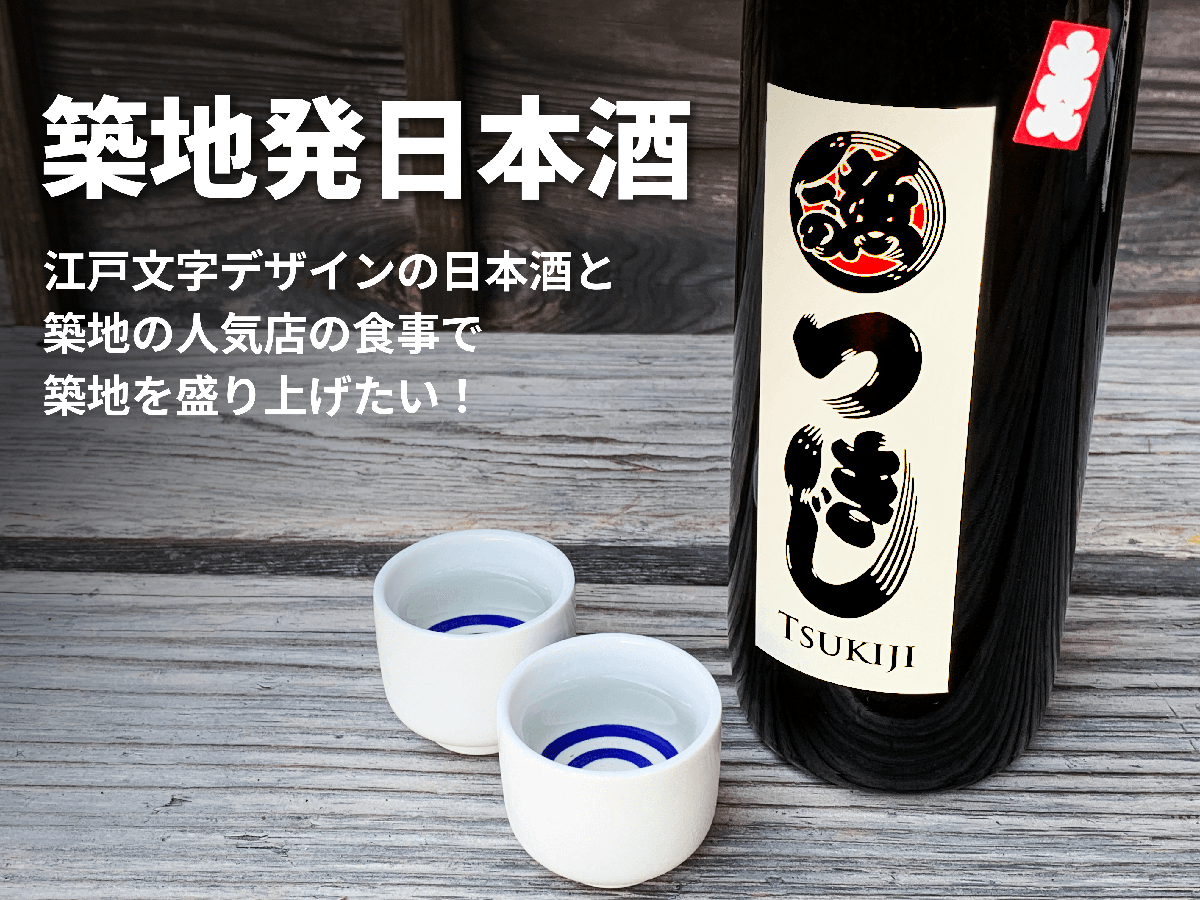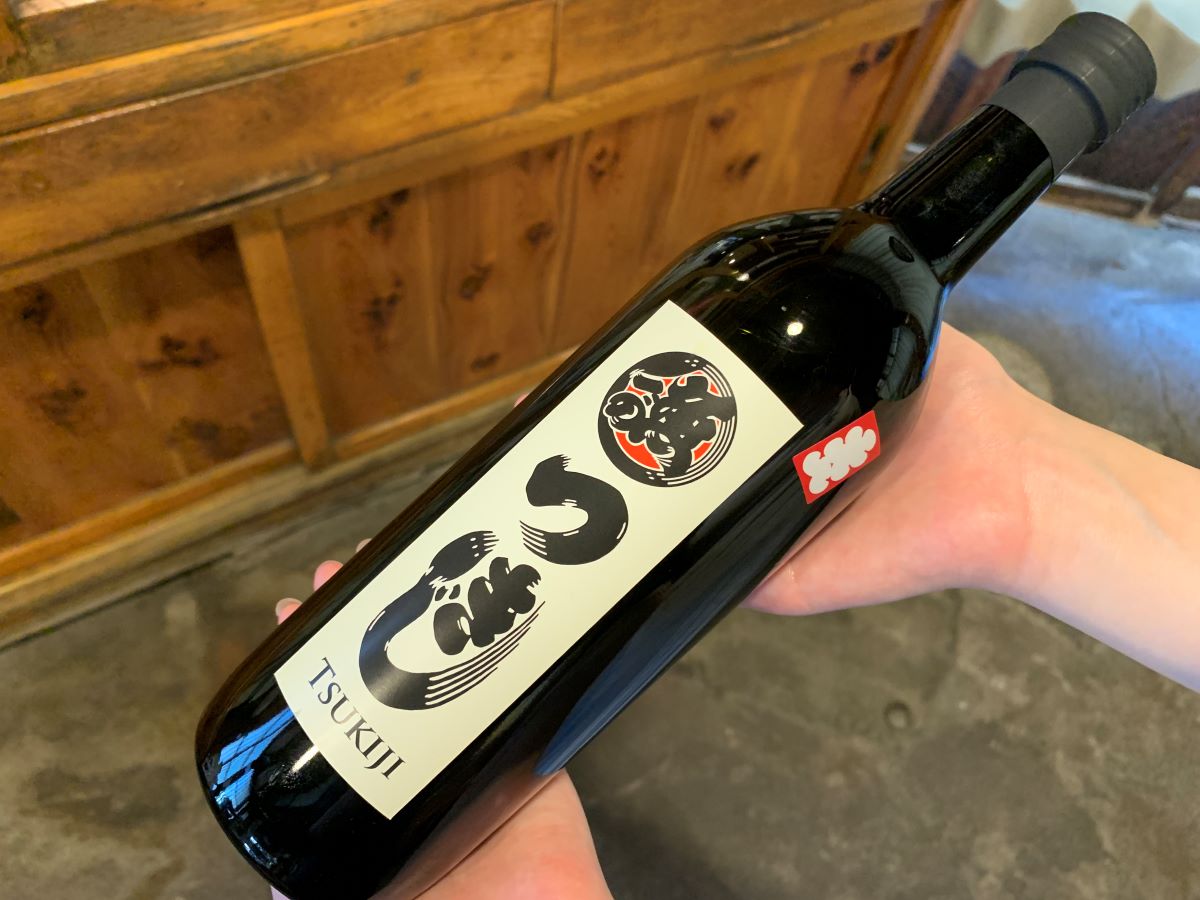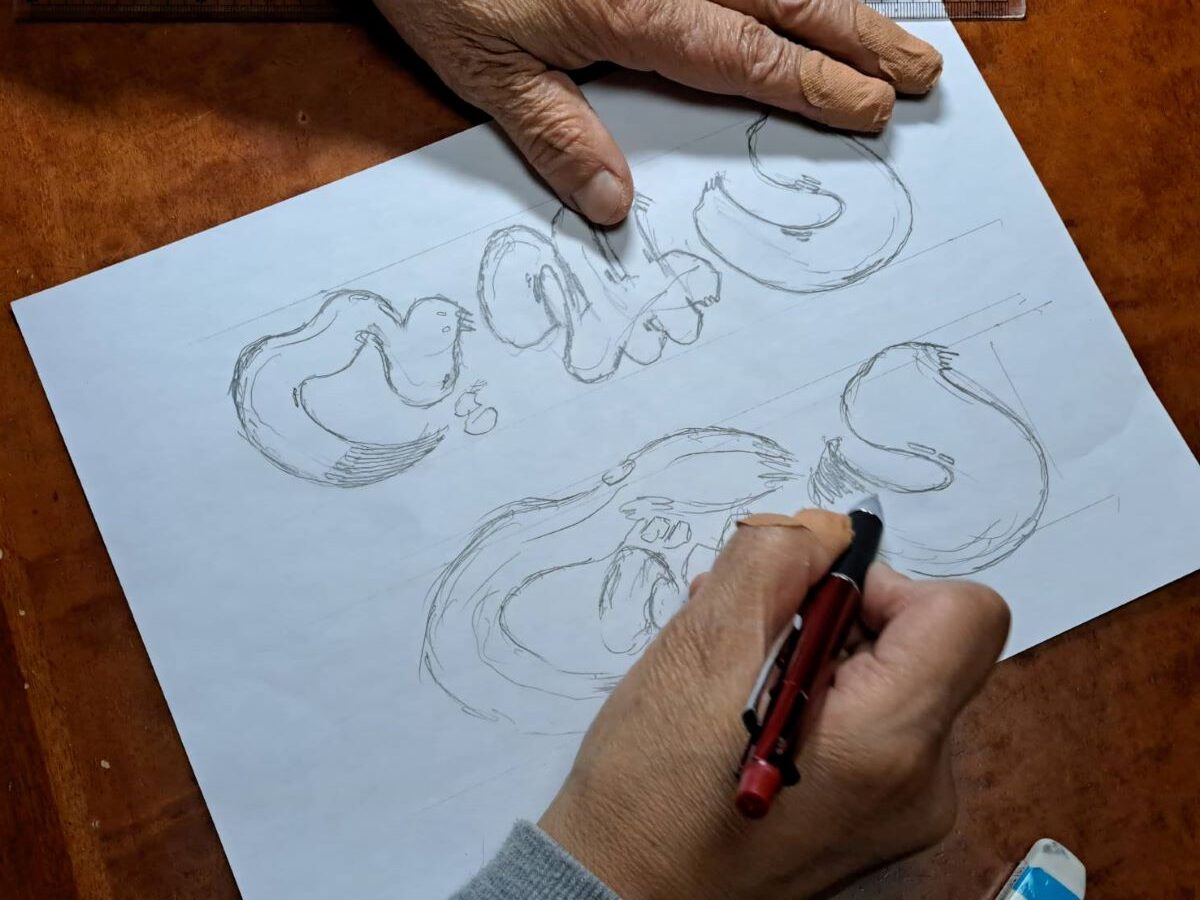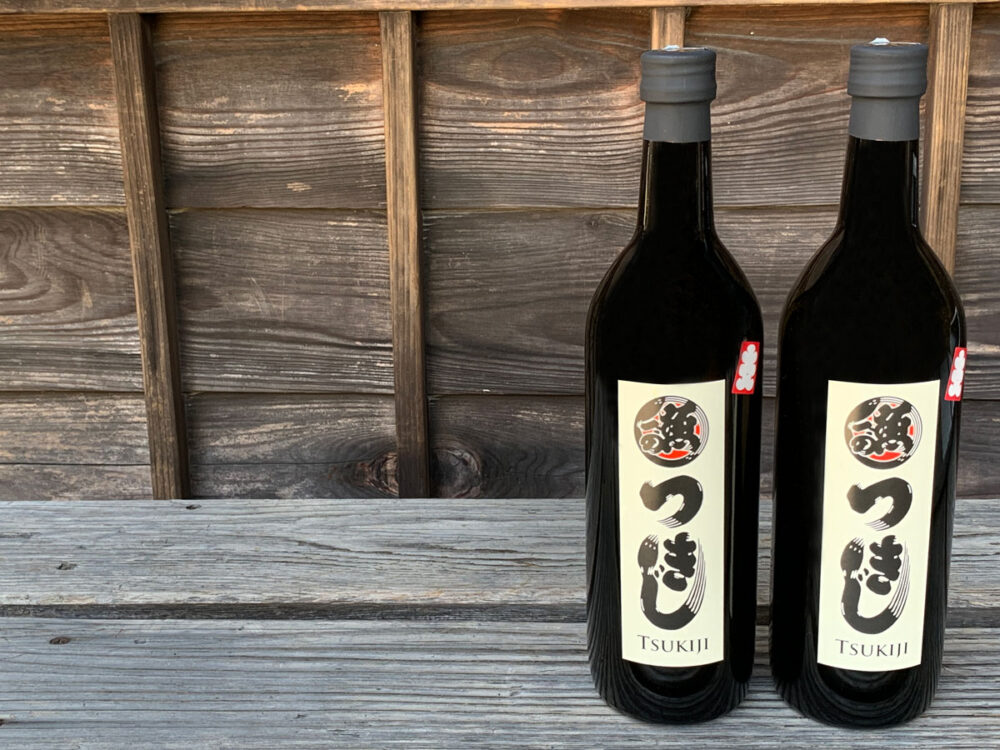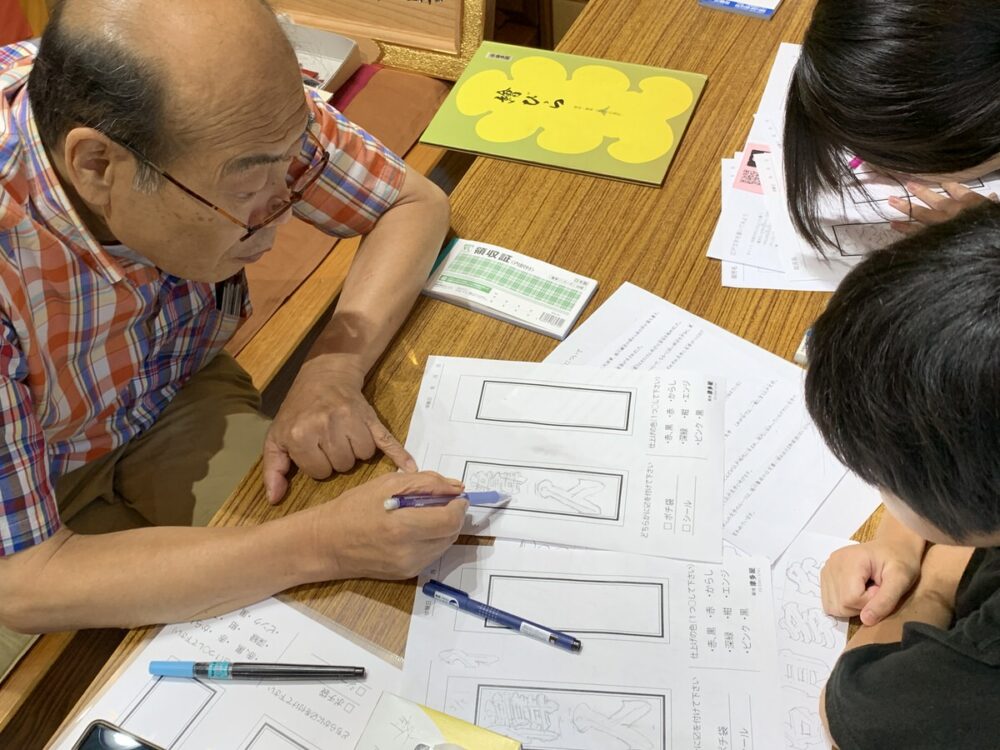
200本完売という「数字」に込められた想い
正直なところ、200本という数字は私たちにとって大きな挑戦でした。
「築地の歴史や文化を応援したい」
「江戸文字でデザインされた日本酒を飲んでみたい」
「築地応援日本酒」のプロジェクトを始めた理由
かつて日本の食文化を支え、活気に満ち溢れていた築地市場。
「築地市場の歴史を未来へと繋ぎ、多くの人々に築地の魅力を再認識してほしい!」そんな願いを込めて、企画された日本酒です。
瓶のラベルには築地で活躍する職人が描かれた江戸文字です。
築地の看板を手がける職人による、力強くも粋な文字は、まさに築地そのもの。
このラベルを制作していただくことで、職人の伝統技術を後世へとつなげます。
お酒を造ってくださるのは、日本酒の醸造に定評のある日光の蔵元です。
その蔵元に、お酒の売上を還元することで、伝統的な酒造りを応援します。
また、私たちの日本酒を築地の飲食店でご提供いただくことで、お店の活性化にも貢献します。
さらに、江戸文字の文化を多くの方に知っていただくため、江戸文字体験と展覧会を開催します。
展覧会は協賛企業のご協力のもと開催することで、企業の活動を広くPRする機会を創出します。
完売した「純米吟醸つきじ」の魅力
築地と日光。
一見、遠く離れた二つの場所が、温かい絆で結ばれています。
蔵元の身内の方が築地に住まわれていて、江戸文字職人さんとの日々の親交を経て、今回のプロジェクトは始まりました。
天保13年(1842年)の創業より日光の地で歴史を刻む蔵元、「渡邊佐平商店さん(わたなべさへいしょうてん)」です。
栃木県日光市に位置する渡邊佐平商店さんは、豊かな自然に恵まれた環境で、代々受け継がれてきた伝統的な酒造りを守り続けています。
日本酒に使われている仕込み水には、日光の豊かな自然で育まれた清らかな伏流水を使用しています。
この清冽な水が、日本酒にまろやかさと深みを与えます。
そして、最も古い歴史を持つ酒米の「雄町(おまち)」を100%使用しました。
雄町は、その栽培の難しさから“幻の酒米”とも言われる希少な米ですが、そこから生まれる酒は、バランスの良い酸味と、透明感のある味わいが特徴です。
口に含むと、雄町特有の華やかで穏やかな香りが広がり、なめらかな口当たりと共に、米の持つ豊かな旨みがじんわりと舌の上に広がります。
刺身や寿司はもちろん、肉料理とも見事に調和し、食卓を一層豊かなものにしてくれます。
子どもたちに「江戸文字」の素晴らしさを伝えたい
今回のプロジェクトの寄付の一部を、子どもたちへの江戸文字体験会の運営費用にも考えています。
子どもたちが、幼い頃から日本の伝統文化に触れ、文字を書く喜び、そして先人たちの知恵と心を感じる機会を提供することで、豊かな感性と創造性を育むことに貢献します。
デジタル世代の子どもたちにとって、手書きの文字は新鮮な体験となります。
集中して、文字を書くことによって、日本の伝統文化への興味関心を深めるきっかけとなり、将来的に文化の継承者となる人材が育つことを心から願っています。
今回、皆様の温かいご支援が、日本の誇るべき伝統文化である江戸文字を未来へ繋ぐ大きな力となります。